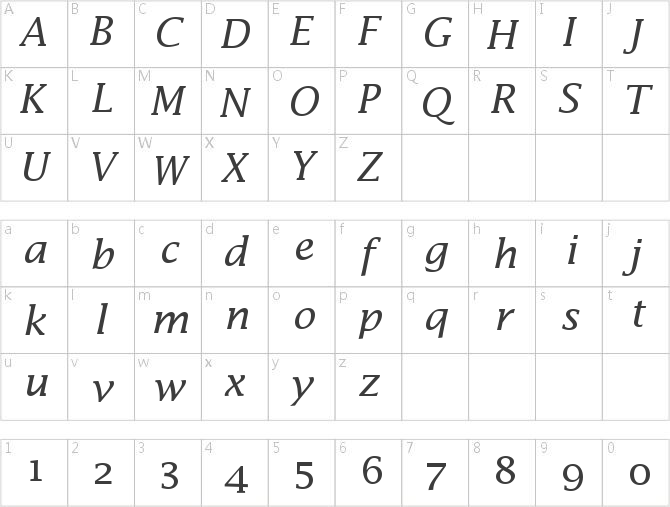
Insight Math Extension SSi 詳情頁
字體名稱: Insight
Insight Math Extension SSi
Insight Math Extension SSi字體字庫是一款讓人賞心悅目、百看不厭的英文字體,適合各類廣告和產品包裝設計應用,字體大小0.03MB,格式為ttf字體,上傳用戶是志誠設計,作者/版權方為未知